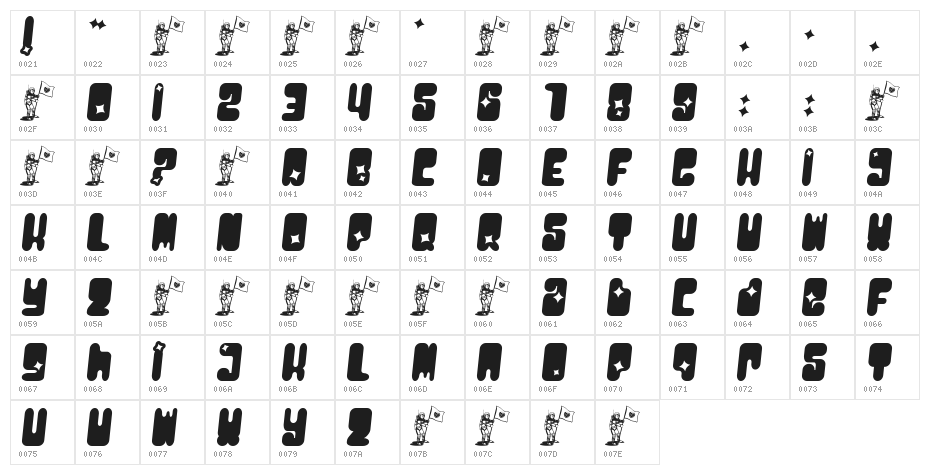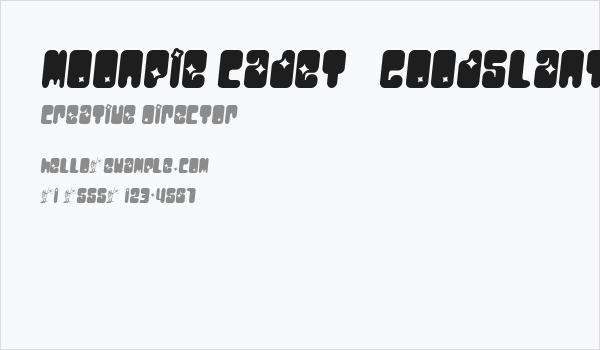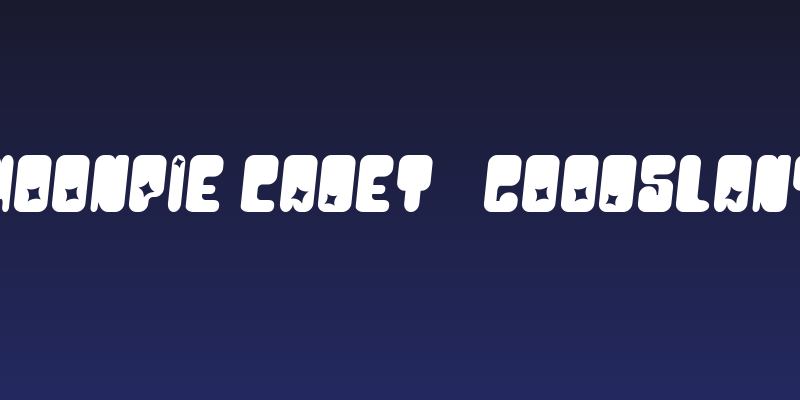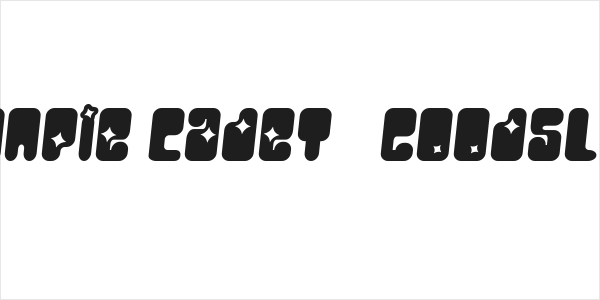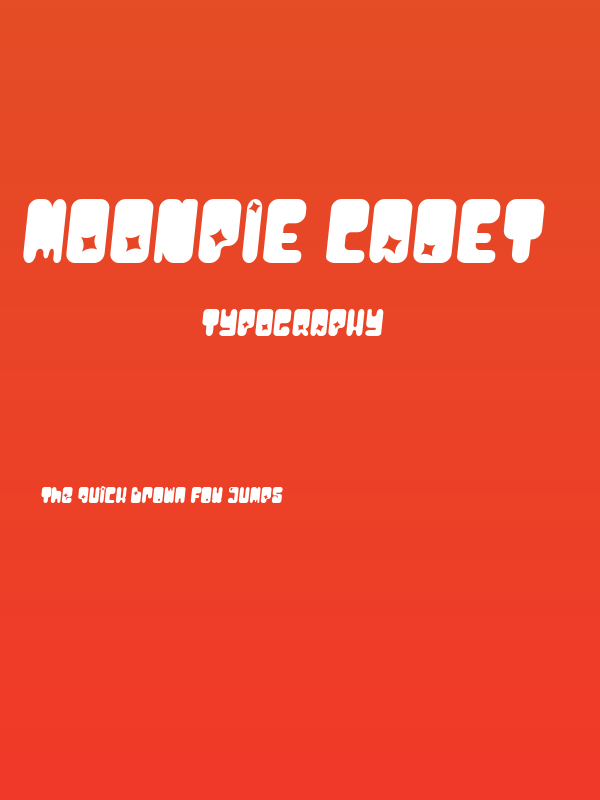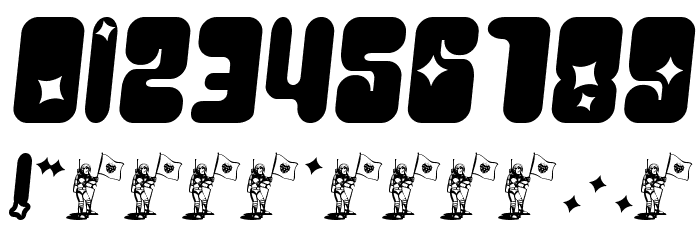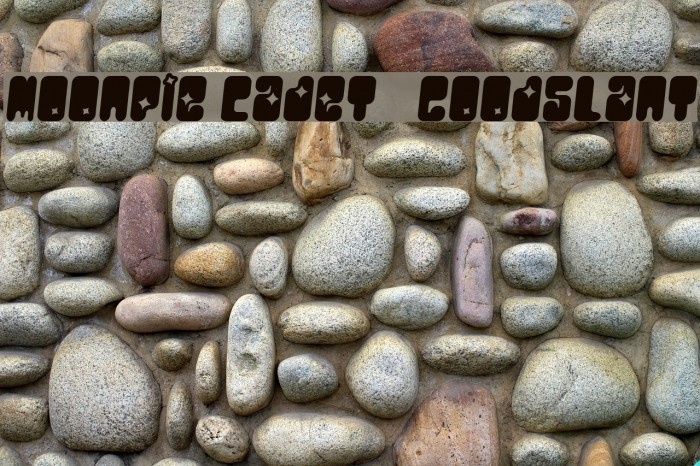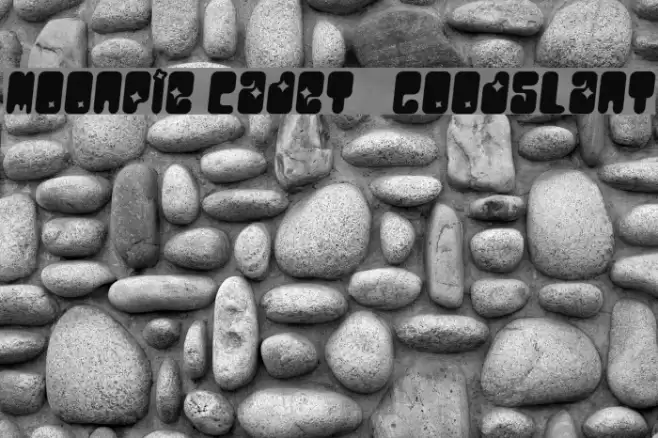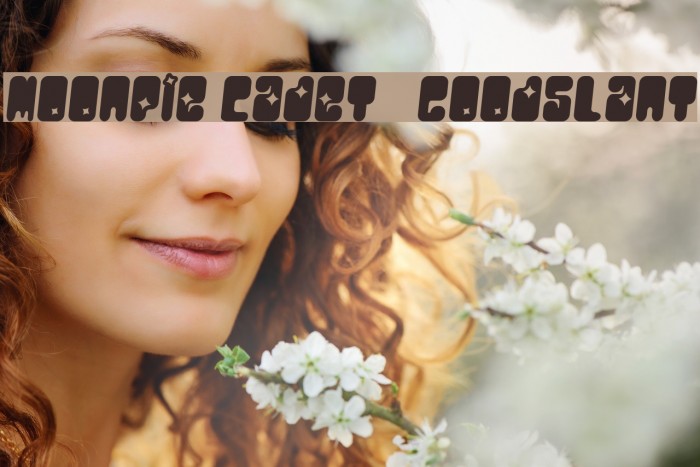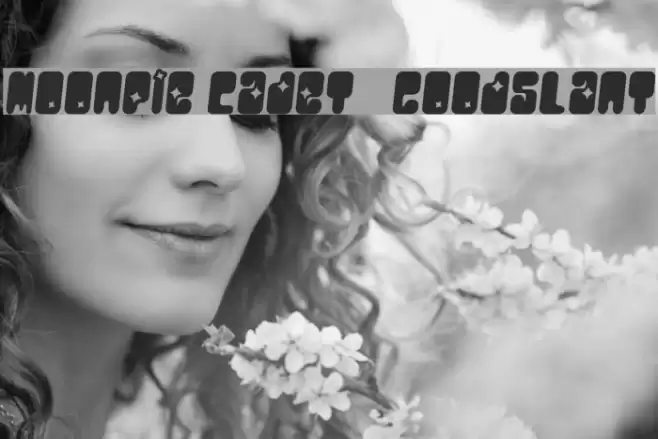
MoonPie Cadet GoodSlant Font
| 全体的なスタイル | Futuristic, Playful, Decorative |
| おすすめプロジェクト | Ideal for sci-fi themed posters, children's book covers, video game titles, and creative branding projects. |